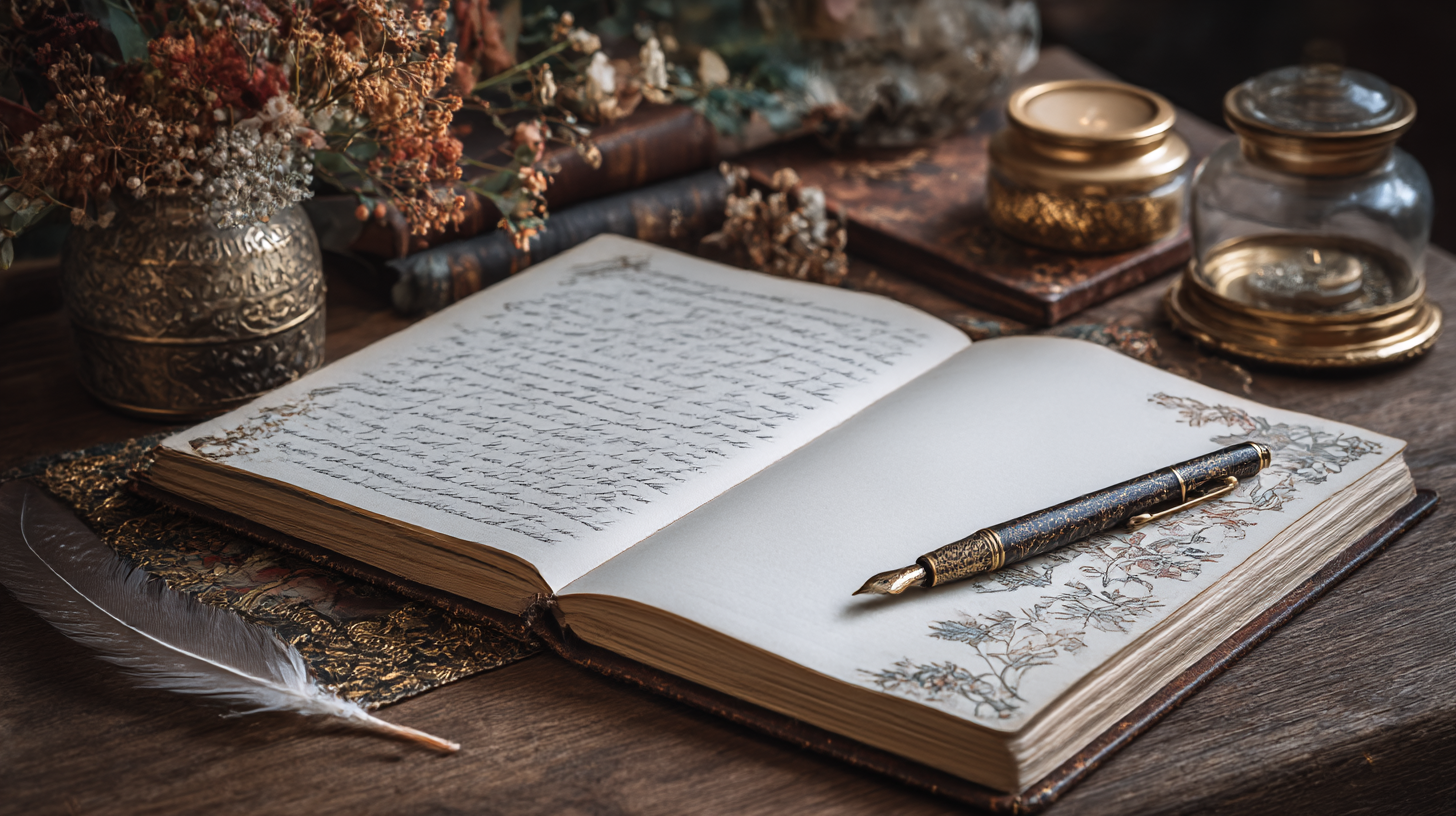
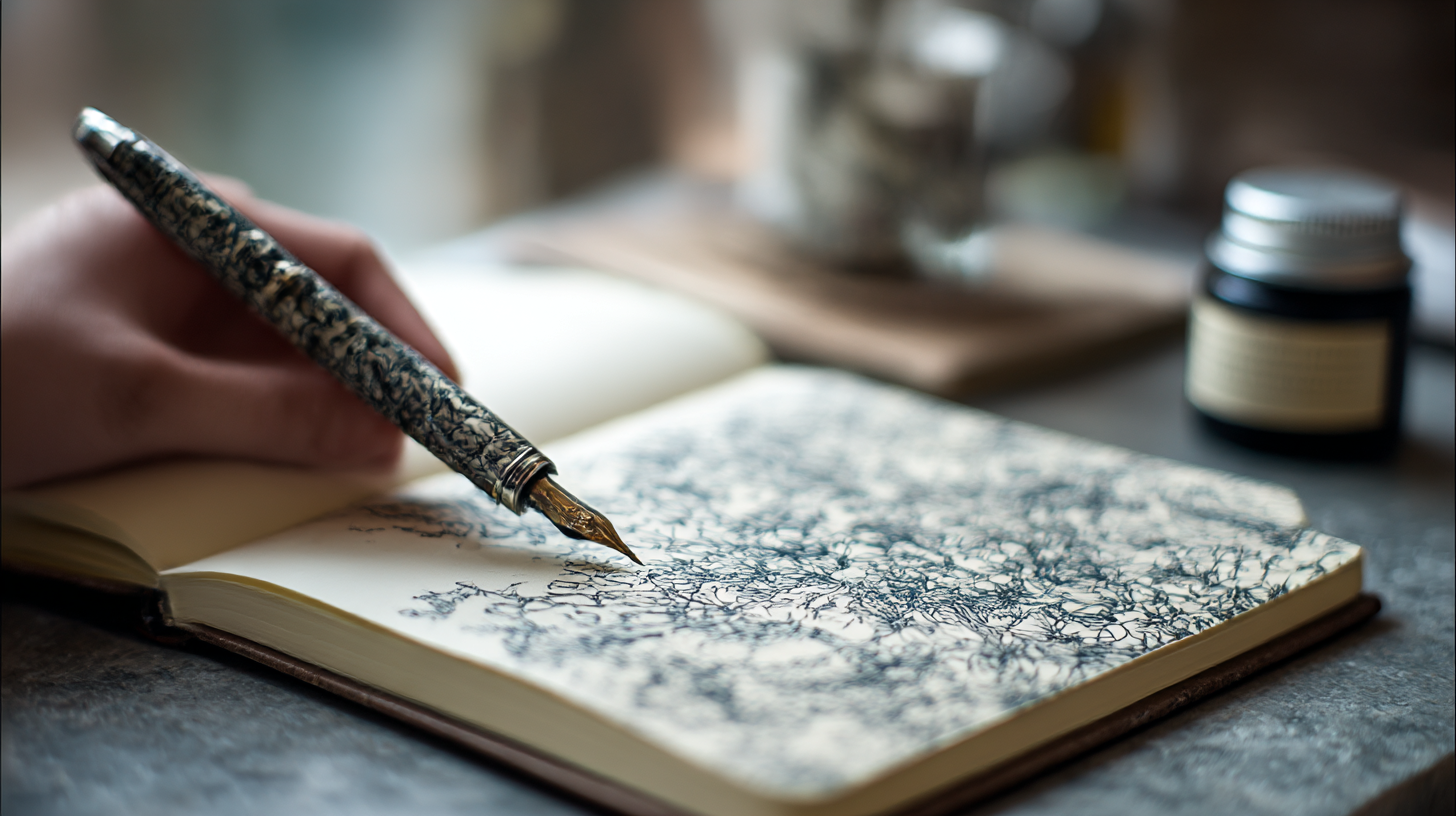
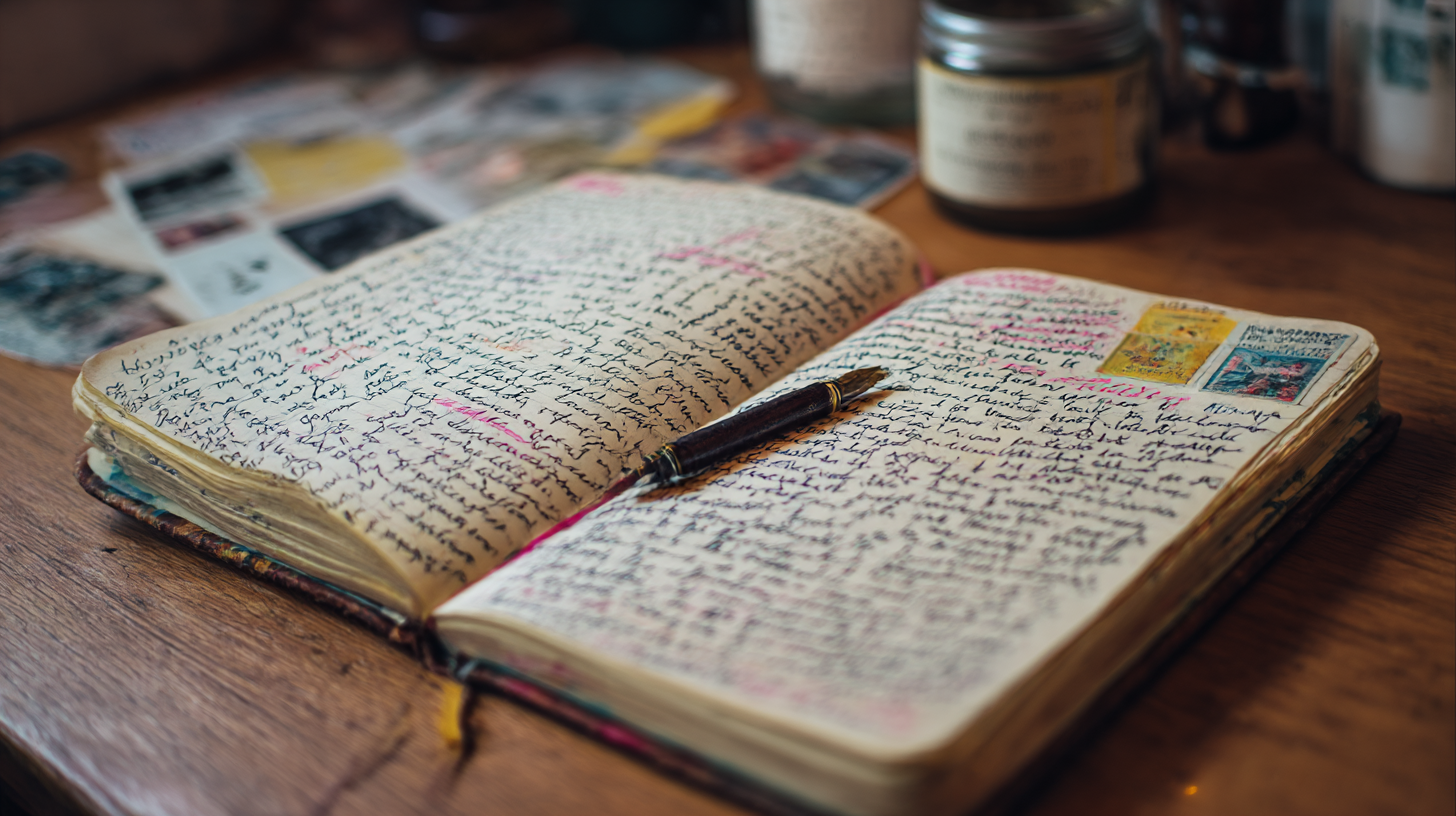
다이어리 꾸미기 좋은 감성 필기 스타일 📖 다이어리를 꾸미면서 감성적인 필기를 하면 일상의 기록이 더욱 특별해져요! 예쁜 글씨와 감각적인 스타일을 적용하면 다이어리를 더욱 아기자기하게 만들 수 있답니다. 🎨✨
내가 생각했을 때 감성 필기는 나만의 개성을 담을 수 있는 특별한 필기 스타일이에요. 오늘은 다이어리를 더욱 감성적으로 꾸미는 다양한 필기 스타일과 꿀팁을 알려드릴게요! 🖊💖
먼저, 감성적인 다이어리 필기의 매력부터 살펴볼까요? 👇
📖 다이어리 필기의 매력
다이어리를 꾸미는 것은 단순한 기록이 아니라, 일상을 특별하게 만드는 과정이에요! 예쁜 필기 스타일과 감각적인 꾸미기를 더하면 다이어리가 더욱 따뜻한 감성으로 채워진답니다. ✨
다이어리 필기의 매력을 정리해보면 다음과 같아요.
- 📅 추억 저장 - 하루하루의 감정을 담아 기록할 수 있음
- 🎨 창의력 향상 - 다양한 글씨체와 꾸미기를 활용해 감각적인 스타일 완성
- 📝 정리 습관 형성 - 하루 계획과 목표를 효과적으로 정리
- 💖 마음의 안정 - 예쁜 필기와 꾸미기로 힐링 효과 UP!
📊 일반 필기 vs 감성 필기 비교
구분 일반 필기 감성 필기 글씨 스타일 단순하고 기능적인 필기 예쁘고 개성 있는 필기 색상 활용 단색 펜으로만 작성 컬러펜 & 하이라이터 활용 꾸미기 요소 없음 스티커, 마스킹 테이프 활용 이처럼 감성 필기는 일반 필기보다 더 창의적이고 개성 있는 스타일을 만들 수 있어요! 이제 다이어리에 적용하기 좋은 다양한 필기 스타일을 살펴볼까요? ✍💖
🖋 감성적인 필기 스타일 종류
감성적인 필기는 글씨체, 색감, 꾸미기 요소 등을 활용해 나만의 스타일을 표현하는 것이 중요해요! 어떤 필기 스타일을 선택하느냐에 따라 다이어리의 분위기가 완전히 달라질 수 있답니다. ✨
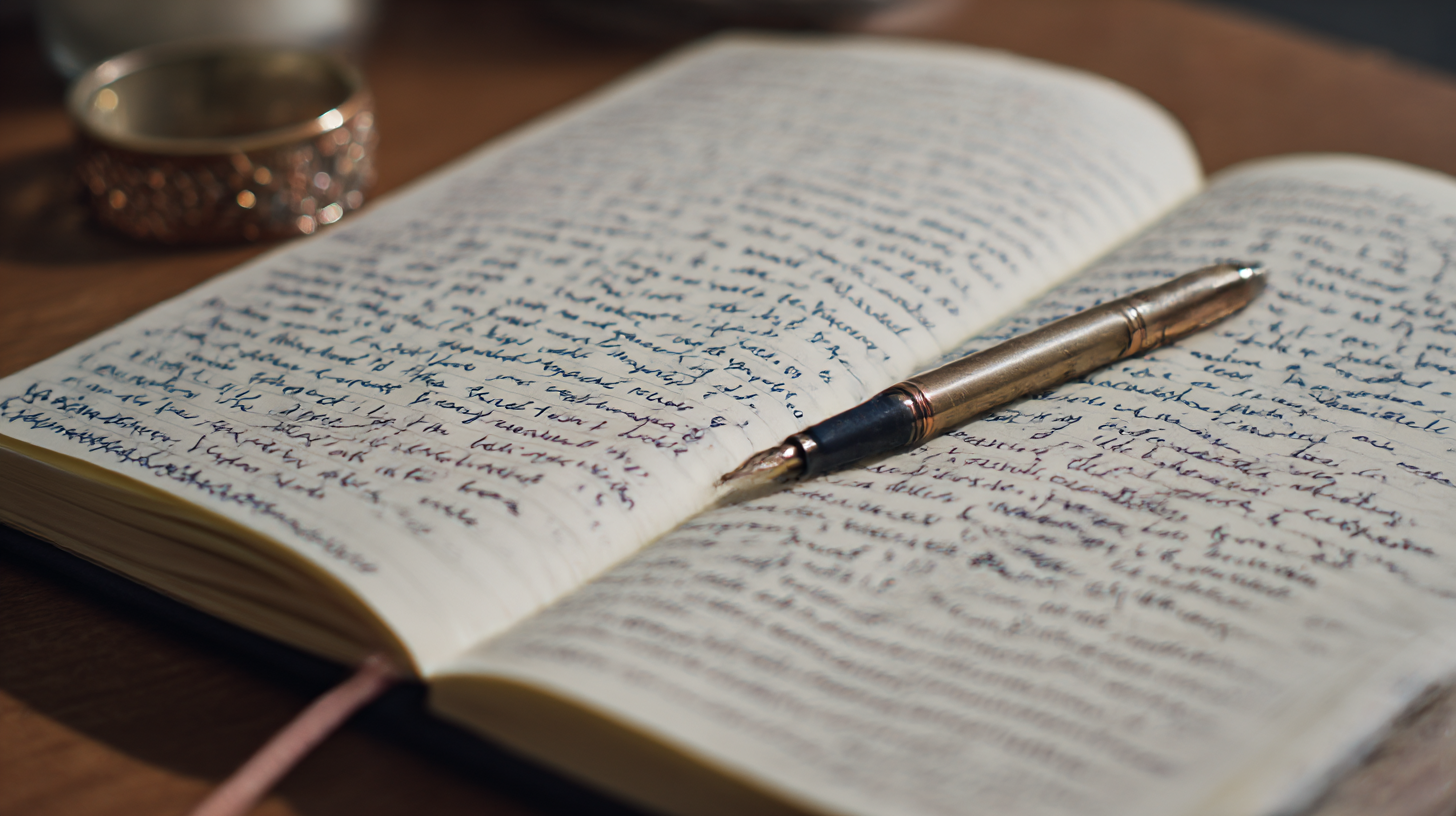
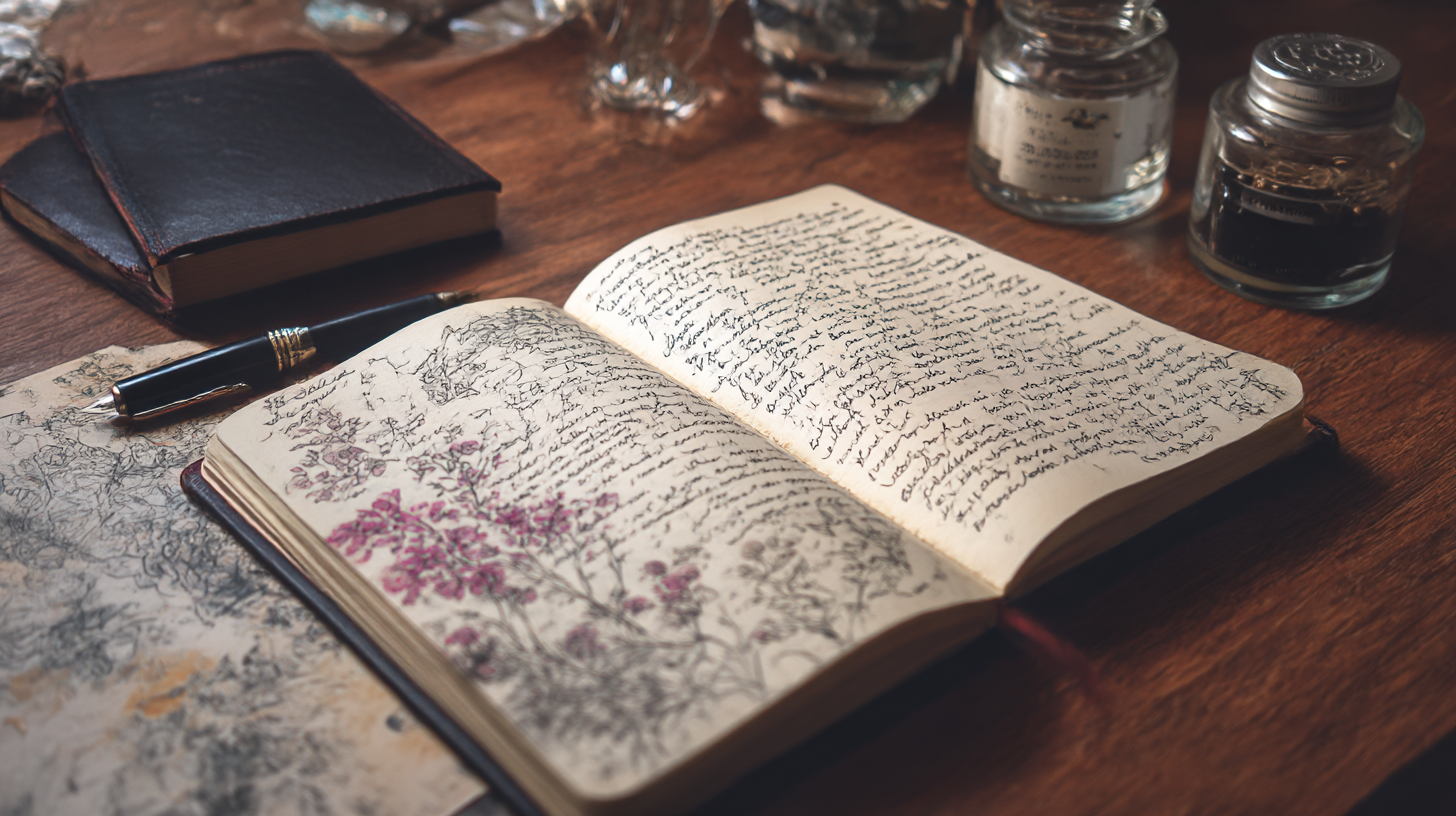
감성적인 필기 스타일 종류 📌 다이어리에 어울리는 감성 필기 스타일
필기 스타일 특징 추천 용도 🖊 미니멀 정자체 깔끔하고 정돈된 느낌 일정 관리, 목표 기록 💖 둥근 감성체 부드럽고 귀여운 느낌 일기 쓰기, 감성 노트 📝 손글씨 흘림체 자연스럽고 흐르는 듯한 스타일 자유로운 필기, 명언 기록 🎨 캘리그래피 스타일 필압을 조절해 강약을 살린 스타일 제목 강조, 다이어리 꾸미기 이처럼 다이어리에 따라 다양한 필기 스타일을 활용할 수 있어요! 이제 감성 필기를 연습하는 방법을 알아볼까요? ✍✨
✍ 감성 필기 연습법
감성 필기는 단순한 글씨 연습이 아니라, 나만의 개성을 담아 표현하는 과정이에요. 따라서 연습할 때는 획을 조절하거나 꾸미기 요소를 함께 활용하는 것이 좋아요! 🎨✨
📌 단계별 감성 필기 연습법
연습 단계 설명 추천 도구 1단계: 선 & 획 연습 직선, 곡선, 점선 등 다양한 선을 일정하게 그려보기 연필, 모눈 노트 2단계: 글자 크기 & 간격 맞추기 글자의 높이, 너비, 자간을 일정하게 유지하는 연습 도트 그리드 노트 3단계: 필기 스타일 적용 정자체, 둥근체, 흘림체 등 원하는 스타일로 연습 젤펜, 만년필 4단계: 꾸미기 요소 추가 스티커, 마스킹 테이프, 컬러펜을 활용해 꾸미기 마일드라이너, 색연필 이 과정을 거치면 점점 나만의 감성적인 필기 스타일이 완성될 거예요! 이제 다이어리를 더욱 특별하게 꾸미는 포인트도 알아볼까요? 🎨✨
🎨 다이어리를 꾸미는 포인트
다이어리를 더욱 감성적으로 꾸미기 위해서는 필기 스타일뿐만 아니라 다양한 꾸미기 요소를 활용하는 것이 중요해요. 글씨뿐만 아니라 색상, 스티커, 마스킹 테이프 등을 적절히 활용하면 더욱 예쁘고 완성도 높은 다이어리를 만들 수 있답니다. ✨
📌 다이어리를 꾸미는 5가지 핵심 요소
꾸미기 요소 활용 방법 🖊 다양한 필기 스타일 정자체, 흘림체, 캘리그래피 등을 섞어 사용하면 다이어리가 더욱 감각적으로 변해요. 🌈 컬러펜 활용 마일드라이너, 색연필 등을 이용해 포인트를 주면 가독성이 높아지고 감성적인 분위기를 연출할 수 있어요. 📌 마스킹 테이프 페이지 테두리를 장식하거나 중요한 부분을 강조하는 용도로 활용하면 다이어리가 더욱 풍성해져요. 📍 스티커 활용 일정 스티커, 감성 일러스트 스티커를 사용하면 다이어리가 더욱 개성 있게 꾸며져요. 🖼 간단한 드로잉 작은 아이콘이나 낙서를 추가하면 다이어리가 더욱 아기자기한 느낌이 들어요. 이렇게 다양한 꾸미기 요소를 활용하면 더욱 감성적이고 나만의 개성이 담긴 다이어리를 만들 수 있어요! 이제 감성 필기에 추천하는 필기구도 함께 살펴볼까요? 🖊✨
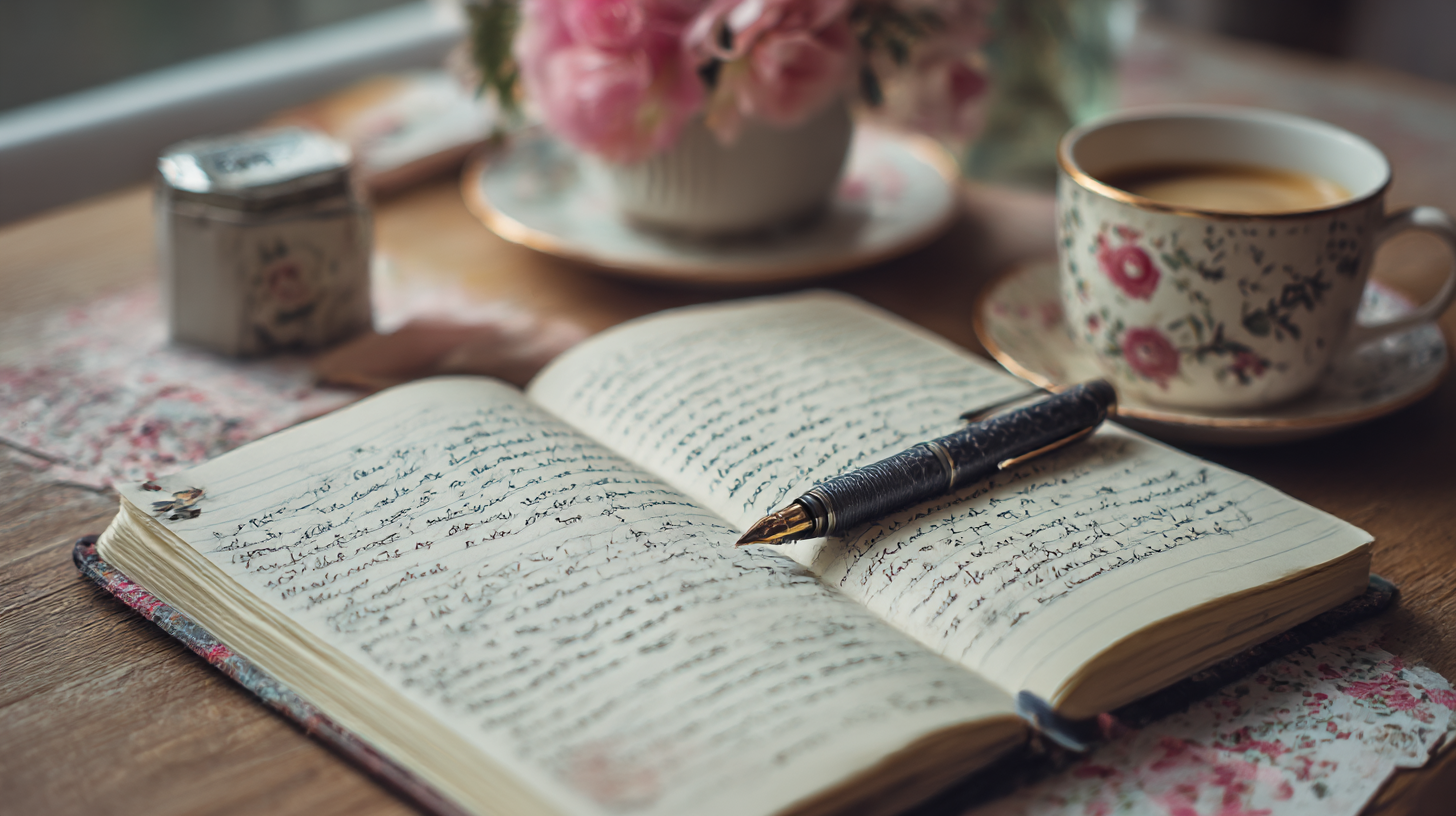
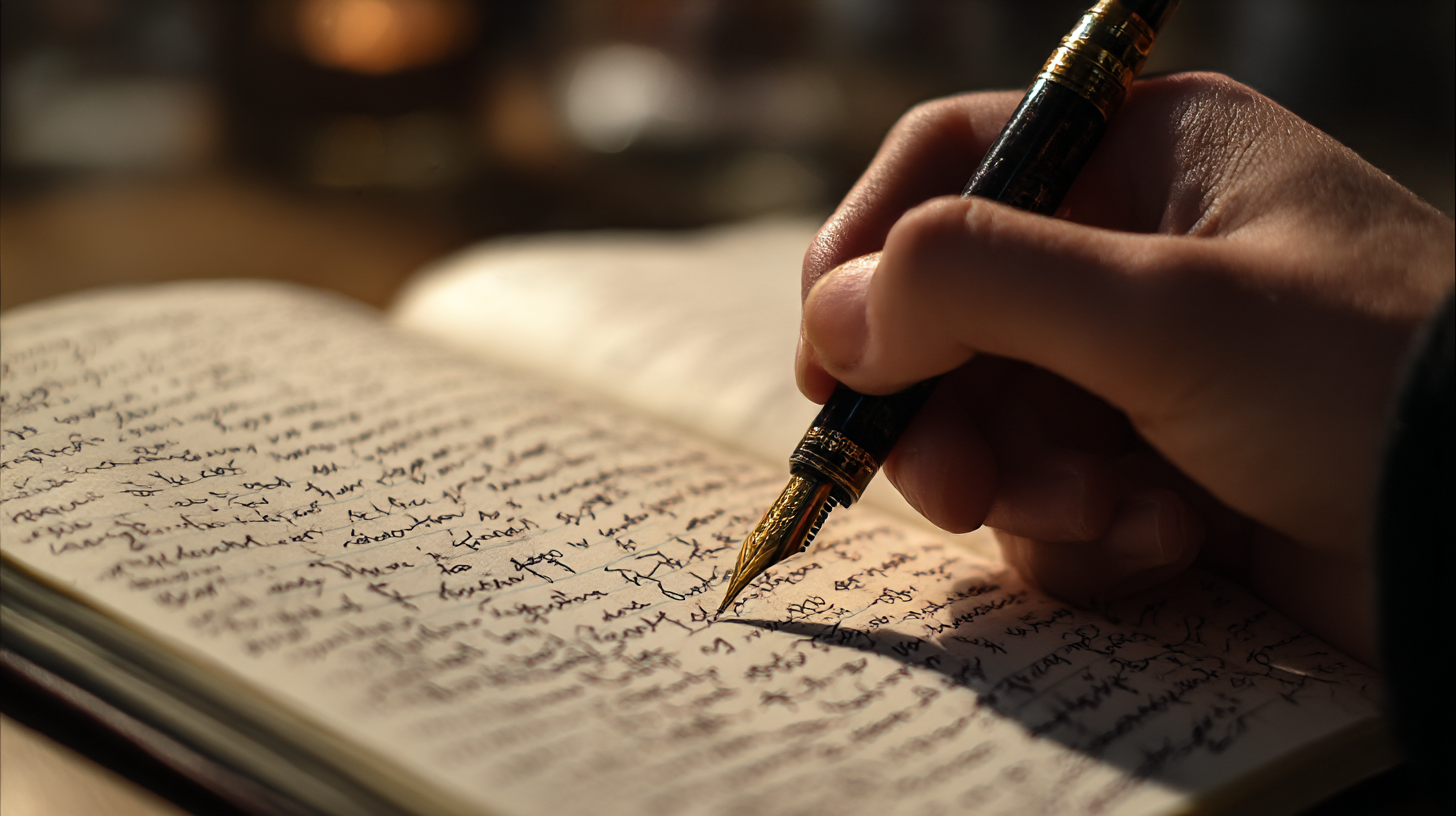
다이어리를 꾸미는 포인트 🖊 감성 필기에 추천하는 필기구
감성적인 다이어리를 꾸미려면 필기감이 좋은 펜과 꾸미기 도구를 선택하는 것이 중요해요! 아래에서 다이어리 꾸미기에 딱 맞는 필기구들을 추천해드릴게요. ✨
📌 감성 필기에 적합한 필기구 추천
필기구 특징 추천 용도 🖊 유니볼 시그노 0.38 얇고 선명한 필기감 깔끔한 정자체 필기 🖋 펜텔 에너겔 0.5 부드럽고 빠른 필기 흘림체 필기 🖌 텀보우 후데노스케 필압 조절이 쉬운 붓펜 캘리그래피 스타일 🎨 마일드라이너 형광펜 부드러운 파스텔 색감 강조 & 꾸미기 📒 다이어리 꾸미기에 추천하는 도구
도구 특징 추천 활용법 📌 마스킹 테이프 다양한 패턴과 색상 활용 가능 페이지 테두리 꾸미기 📍 감성 스티커 일정 & 장식용으로 활용 가능 포인트 장식 🖼 드로잉 펜 얇은 선을 그리기에 적합 아이콘 & 일러스트 추가 필기구와 꾸미기 도구를 잘 활용하면 더욱 감성적인 다이어리를 완성할 수 있어요! 이제 다이어리를 예쁘게 필기하는 꿀팁도 함께 알아볼까요? ✨
💡 다이어리 필기를 예쁘게 하는 꿀팁
다이어리를 더욱 감성적으로 꾸미려면 몇 가지 필기 & 꾸미기 팁을 적용하는 것이 중요해요! 글씨 크기, 색상, 꾸미기 요소를 적절히 조합하면 훨씬 정돈되고 감각적인 다이어리가 완성된답니다. ✍✨
📌 다이어리 필기를 예쁘게 만드는 5가지 꿀팁
꿀팁 설명 1. 일정한 글씨 크기 유지 글씨 크기가 들쭉날쭉하면 정리가 안 돼 보일 수 있어요. 일정한 크기를 유지하세요. 2. 컬러 조합 맞추기 2~3가지 메인 컬러를 정해 사용하면 다이어리가 더욱 감각적으로 보여요. 3. 포인트 강조하기 제목이나 중요한 내용은 두꺼운 펜이나 하이라이터로 강조하면 좋아요. 4. 꾸미기 아이템 활용 마스킹 테이프, 스티커, 작은 아이콘 등을 적절히 활용하면 감성적인 느낌을 더할 수 있어요. 5. 여백을 적절히 활용 너무 빽빽하게 적기보다는 여백을 살려 가독성을 높이는 것이 중요해요. 이 꿀팁을 적용하면 더욱 예쁘고 정돈된 감성 다이어리를 완성할 수 있어요! 이제 다이어리 필기와 관련된 자주 묻는 질문(FAQ)을 확인해볼까요? 🤔
Q1. 다이어리 필기를 감성적으로 꾸미려면 어떻게 해야 하나요?
A1. 필기 스타일을 다양하게 활용하고, 컬러펜과 스티커, 마스킹 테이프 등을 적절히 조합하면 감성적인 다이어리를 만들 수 있어요. ✨
Q2. 다이어리 필기 스타일이 항상 마음에 안 드는데 개선하는 방법이 있을까요?
A2. 꾸준한 연습이 가장 중요해요! 먼저 정자체 연습부터 시작한 후, 흘림체나 캘리그래피를 추가하면서 점차 스타일을 만들어보세요. ✍
Q3. 다이어리를 꾸밀 때 어떤 색상을 사용하면 좋을까요?
A3. 한 가지 톤을 정해 사용하면 훨씬 감각적인 다이어리가 완성돼요. 예를 들어, 파스텔톤이나 모노톤 등으로 통일감을 주는 것이 좋아요. 🎨
Q4. 다이어리를 꾸밀 때 너무 지저분해 보이지 않게 하는 방법은?
A4. 글씨 크기와 간격을 일정하게 유지하고, 너무 많은 꾸미기 요소를 사용하지 않는 것이 중요해요. 여백을 적절히 활용하면 더 깔끔해 보여요! 🖊
Q5. 추천하는 다이어리 브랜드가 있나요?
A5. 몰스킨, 365 다이어리, 무지 노트, 콕스 다이어리 등 다양한 브랜드가 있어요. 필기 스타일과 꾸미기 취향에 맞춰 선택해 보세요. 📒
Q6. 감성적인 필기를 위해 가장 추천하는 필기구는 무엇인가요?
A6. 유니볼 시그노 0.38(정자체), 펜텔 에너겔 0.5(흘림체), 텀보우 후데노스케(캘리그래피), 마일드라이너(컬러 꾸미기) 조합을 추천해요! 🖋
Q7. 다이어리 속지를 직접 디자인해서 쓰고 싶은데, 좋은 방법이 있을까요?
A7. 무지 노트나 도트 그리드 노트를 활용해 직접 선을 긋고 꾸미면서 나만의 속지를 만들 수 있어요. 디지털로 디자인한 후 출력하는 것도 좋아요. 📄
Q8. 다이어리를 꾸미는 것이 귀찮은데 간단하게 감성적인 느낌을 내는 방법이 있나요?
A8. 간단한 아이콘을 추가하거나, 제목만 손글씨 스타일로 적고 나머지는 깔끔하게 정리하는 방법을 추천해요. 포인트만 줘도 감성적인 분위기를 낼 수 있어요! 😊